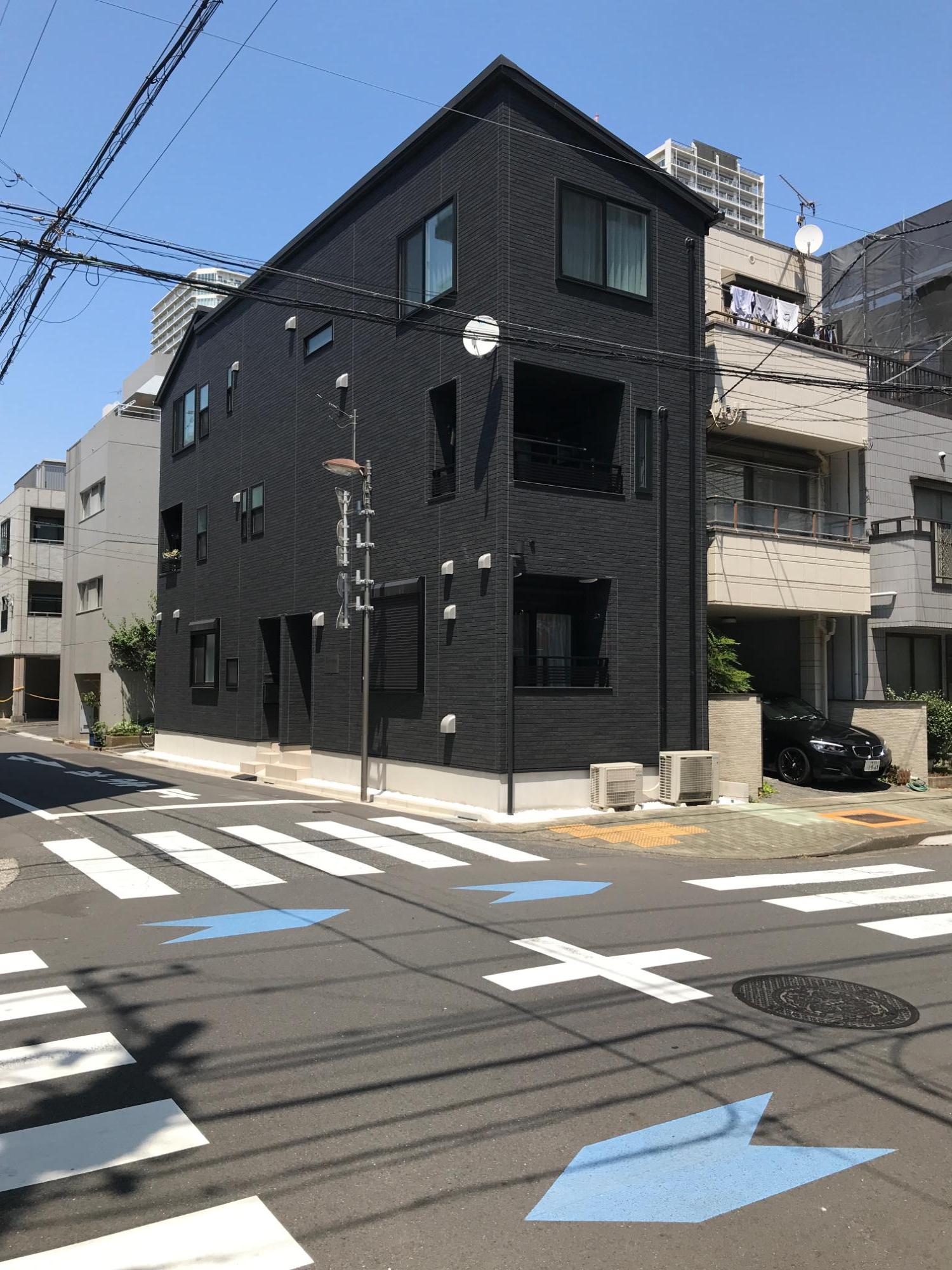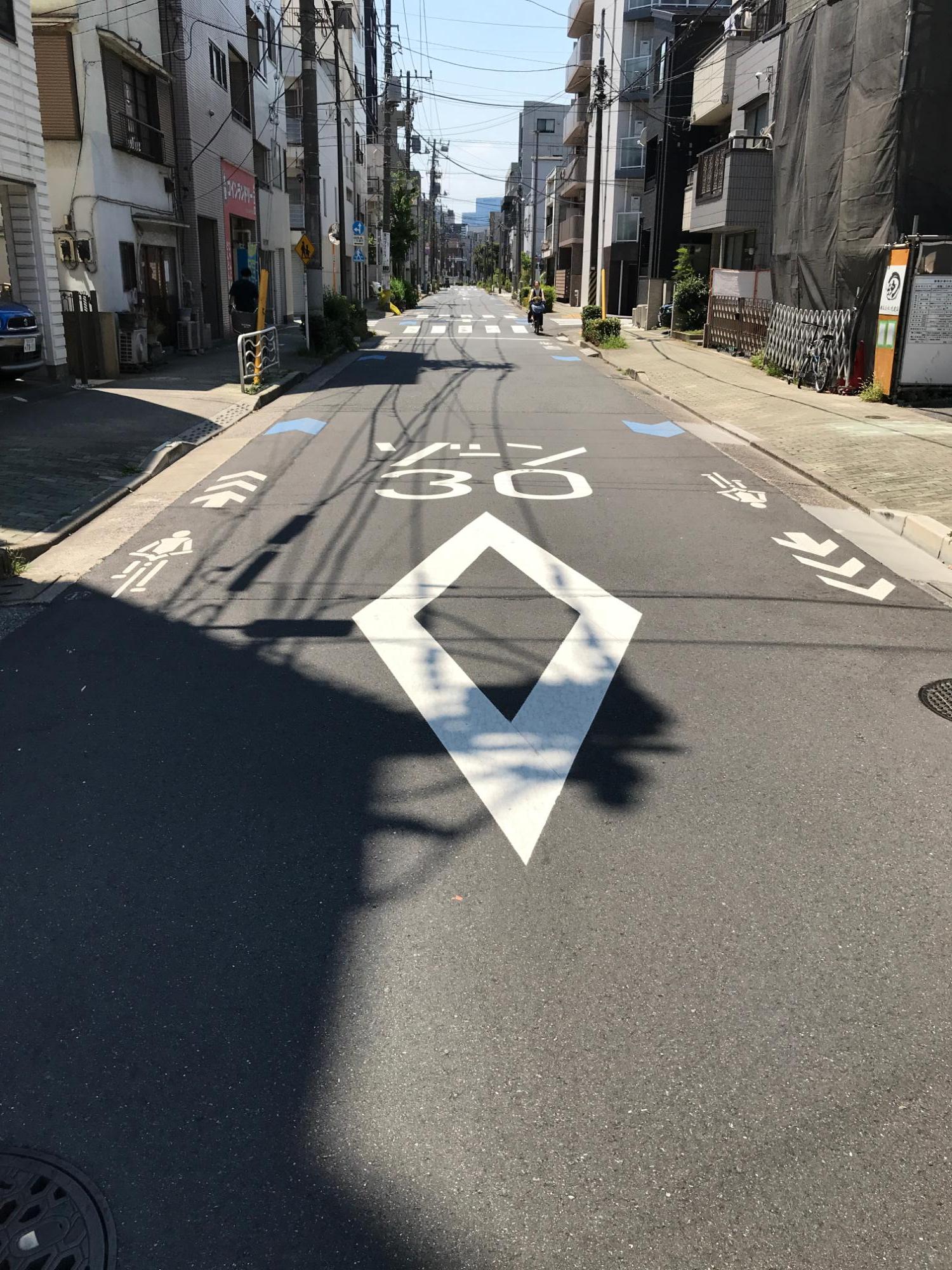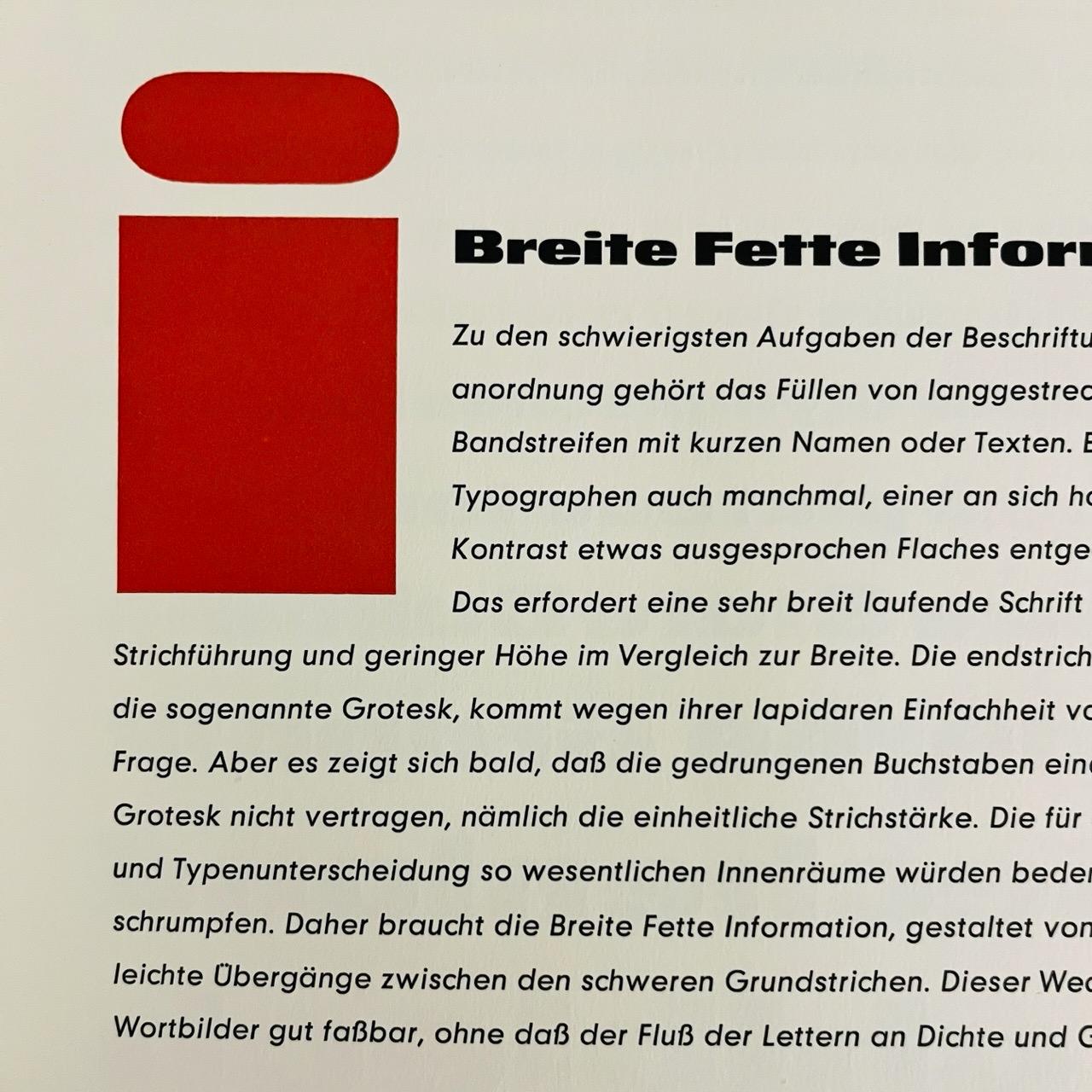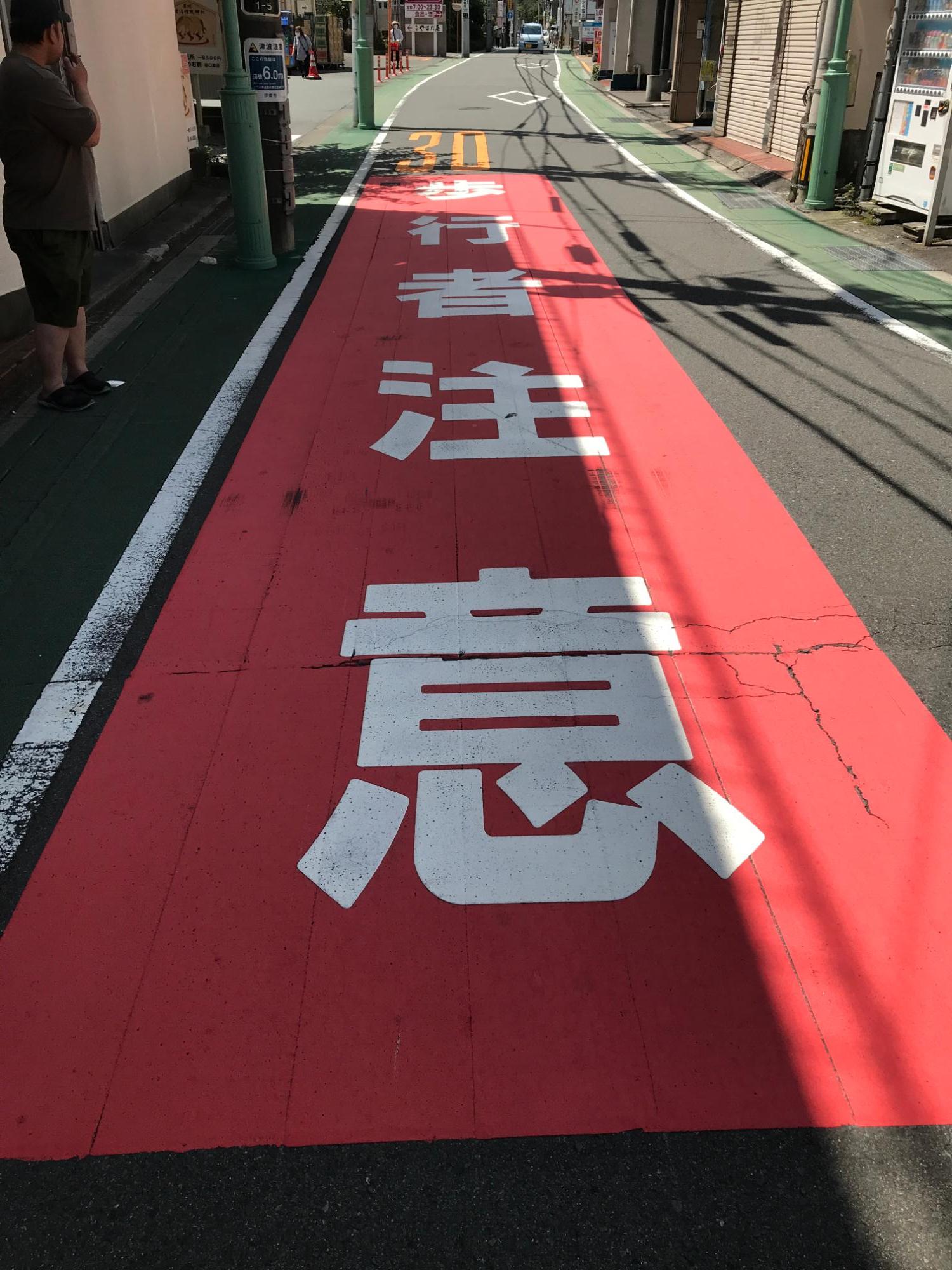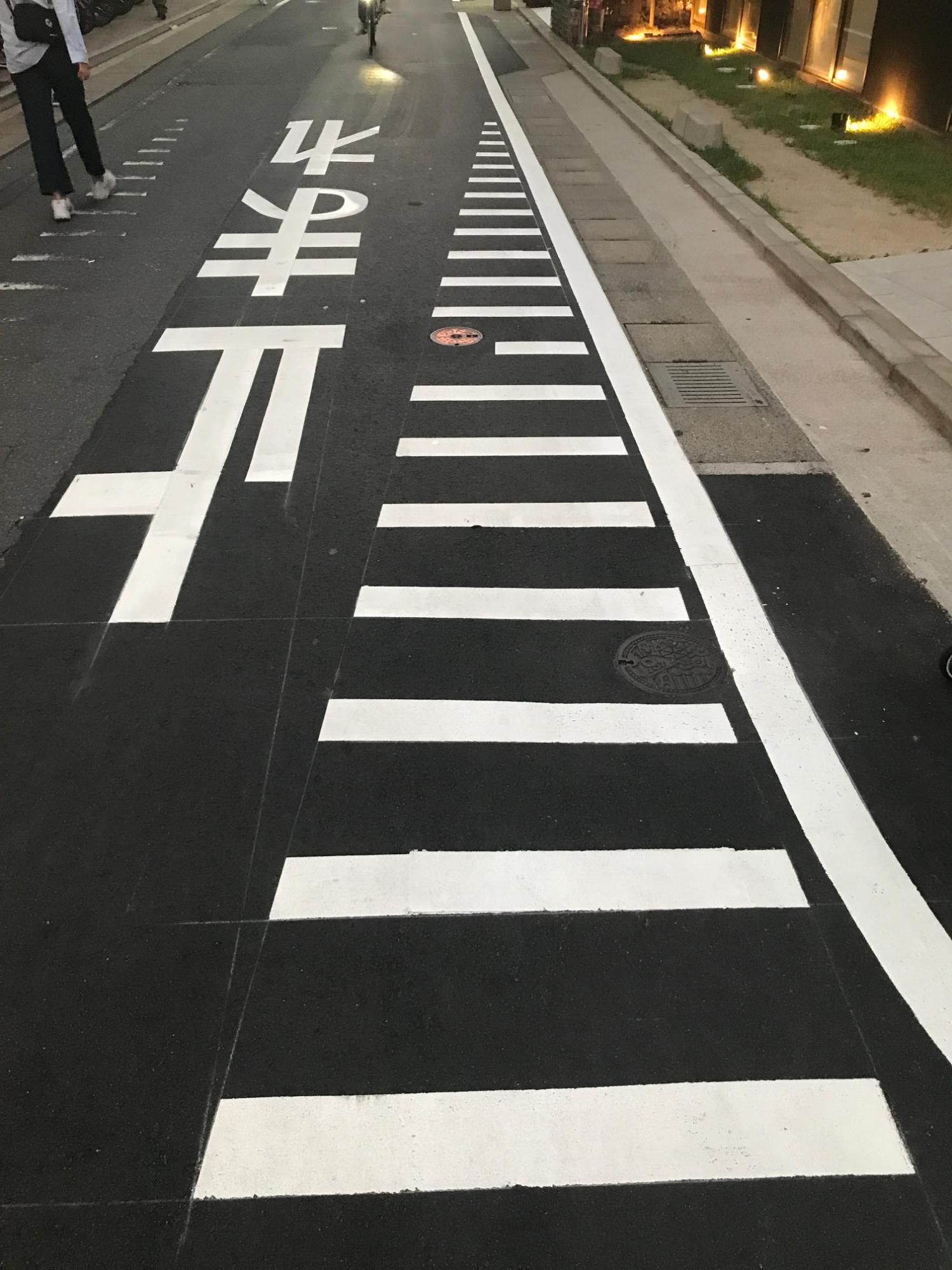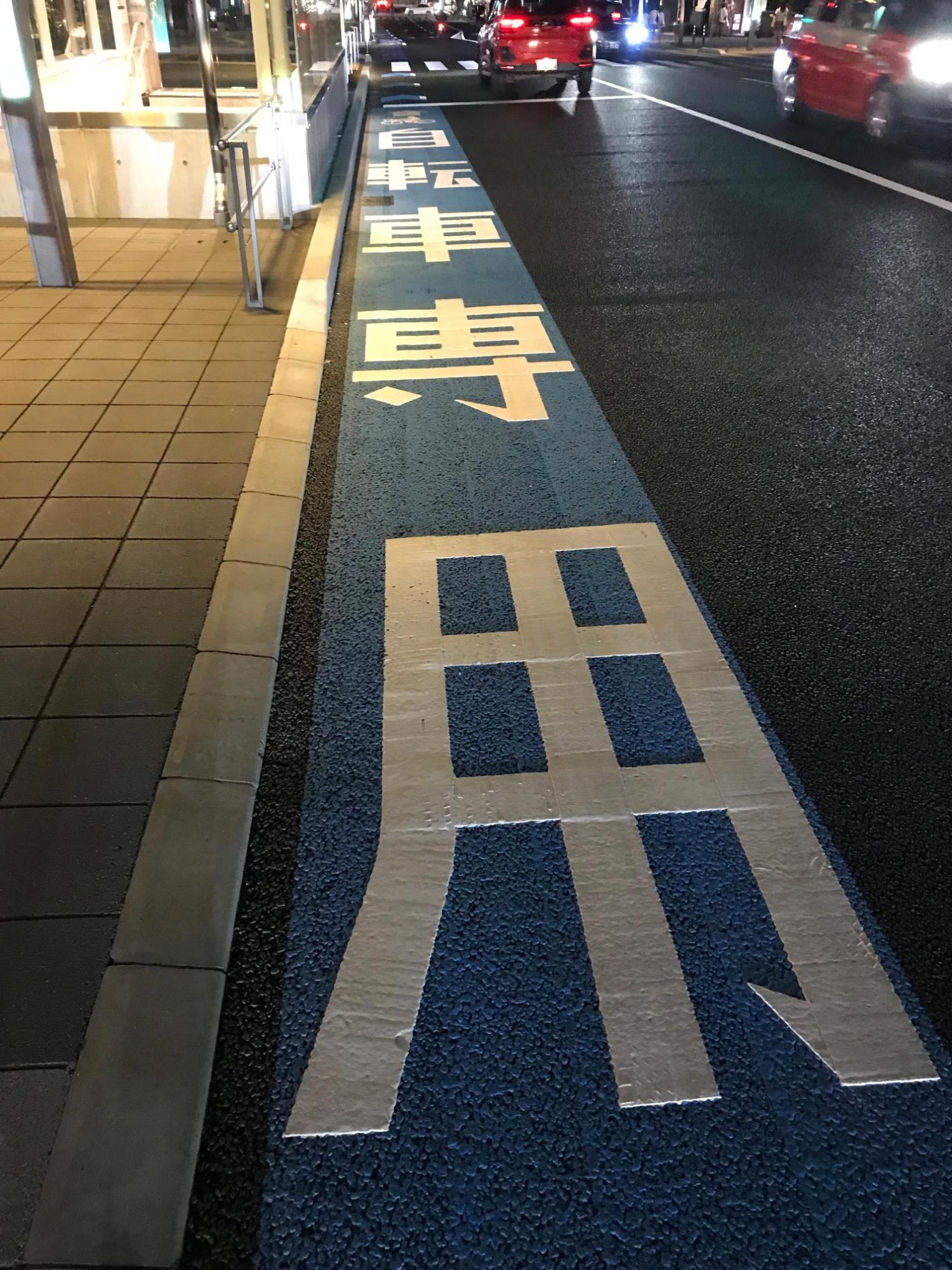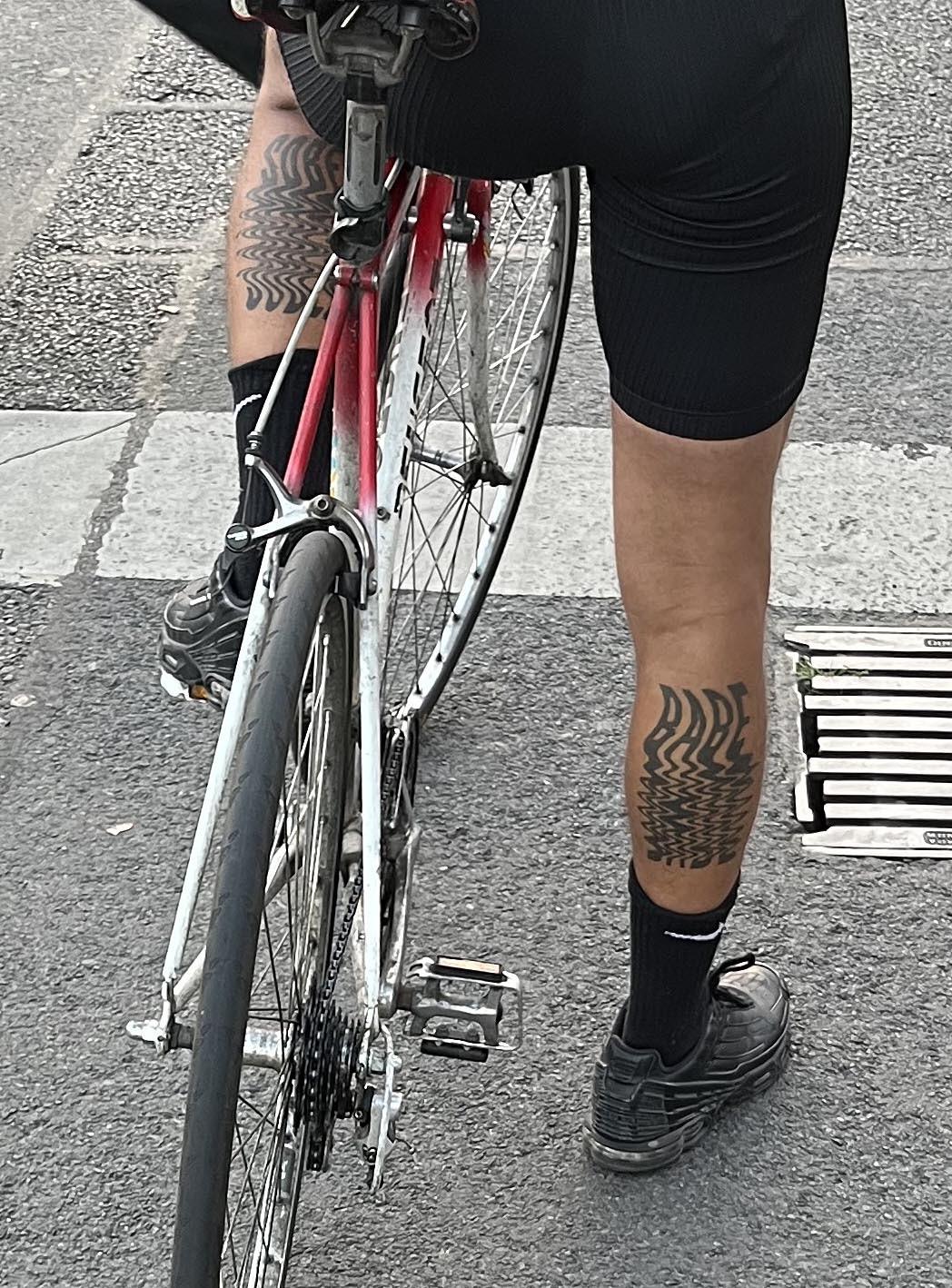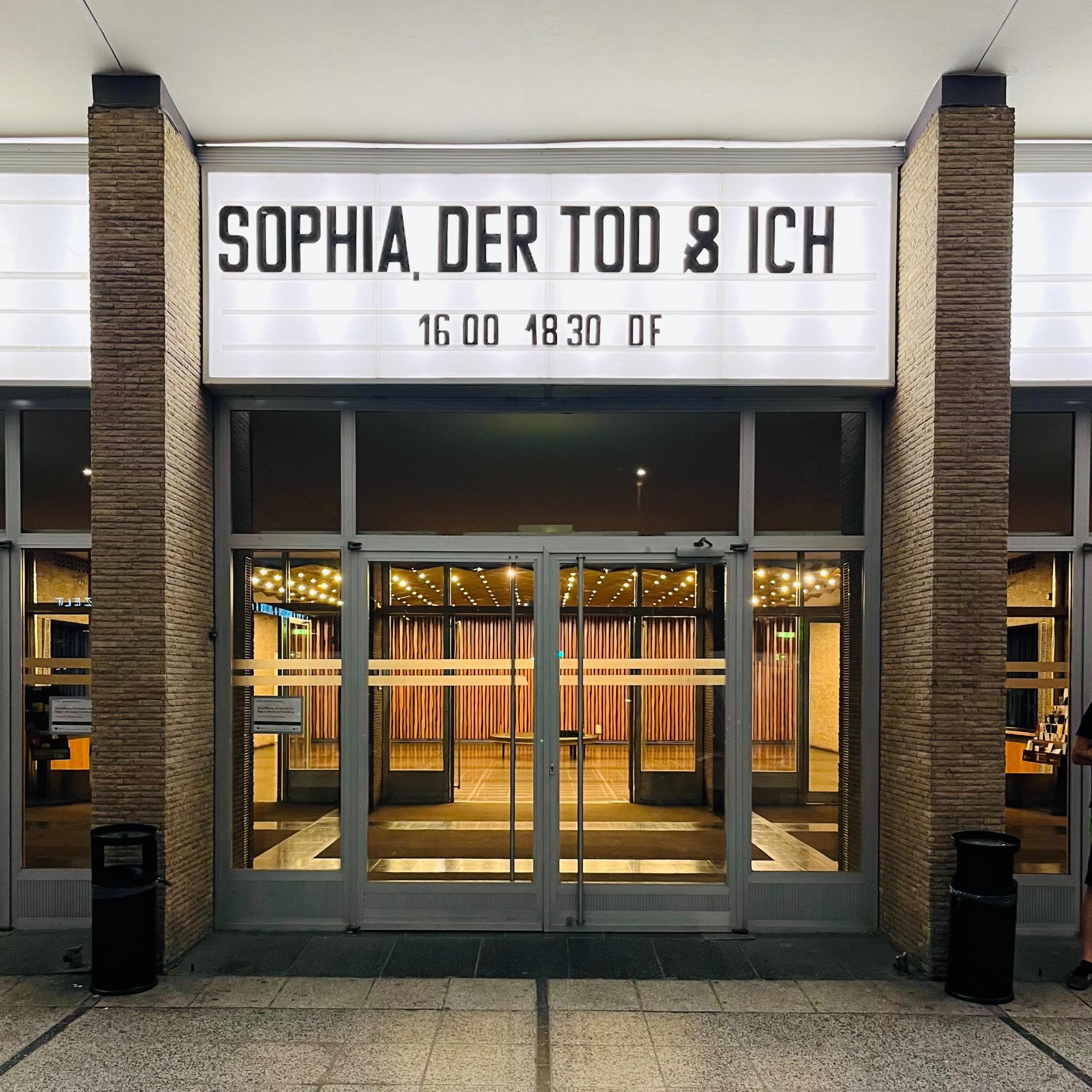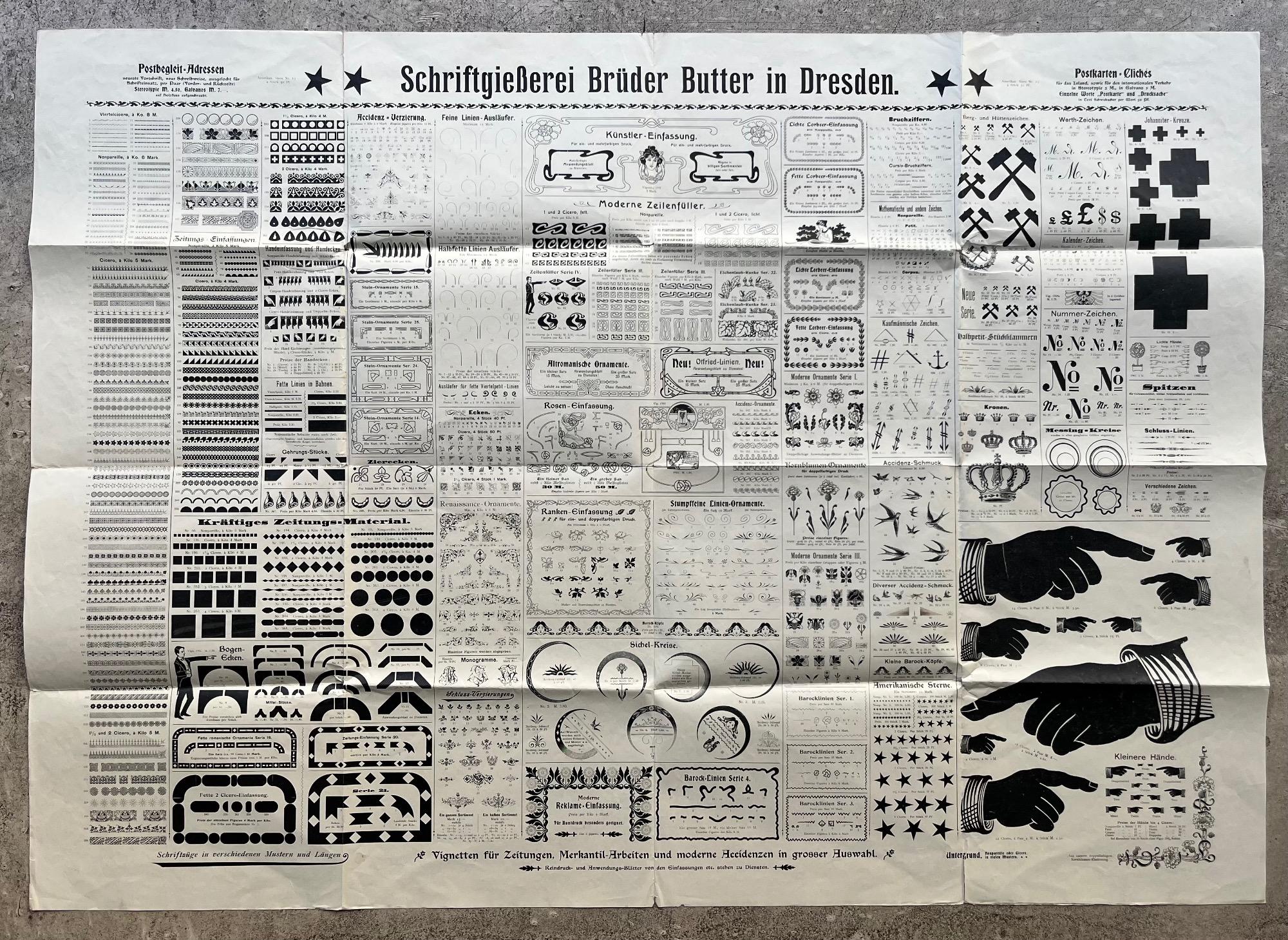
Ähnliches findet man auch in Karlsruhe. In der Klauprechtstraße und Kronenstraße habe ich solche Lettern mit dem markanten kleinen t auf alten Schildern gesehen. Diese basieren auf einer konventionellen Schrift, die ich stilisiert als Schilder Grotesk unter der SIL-OFL nachgebaut habe.
Neulich an der Ampel ... Sober Babe
Wade würde auch passen :-)
IMHO hätte man die Spationierung der »14« optimieren können, fand es aber trotzdem ganz schön …
Noch ein paar weitere Impressionen. Nicht alles formal-ästhetisch reizvoll, aber irgendwie doch faszinierend …
Nicht alles formal-ästhetisch reizvoll, aber irgendwie doch faszinierend …
Mein Favorit ist das letzte Bild ... :rockon:
Soll das ein Komma nach Sophia sein?
Ne Fliege? ;-)
Soll das ein Komma nach Sophia sein?
Ja. Ein sogenanntes »Gaffa-Komma« (oder auch »Duct Tape Comma«) um genau zu sein.
Die »Imbiss-Oase« auf der Karl-Marx-Allee. :biglove:
Leider sehe ich sie nur noch im geschlossenen Zustand, wenn ich da mal vorbeikomme.